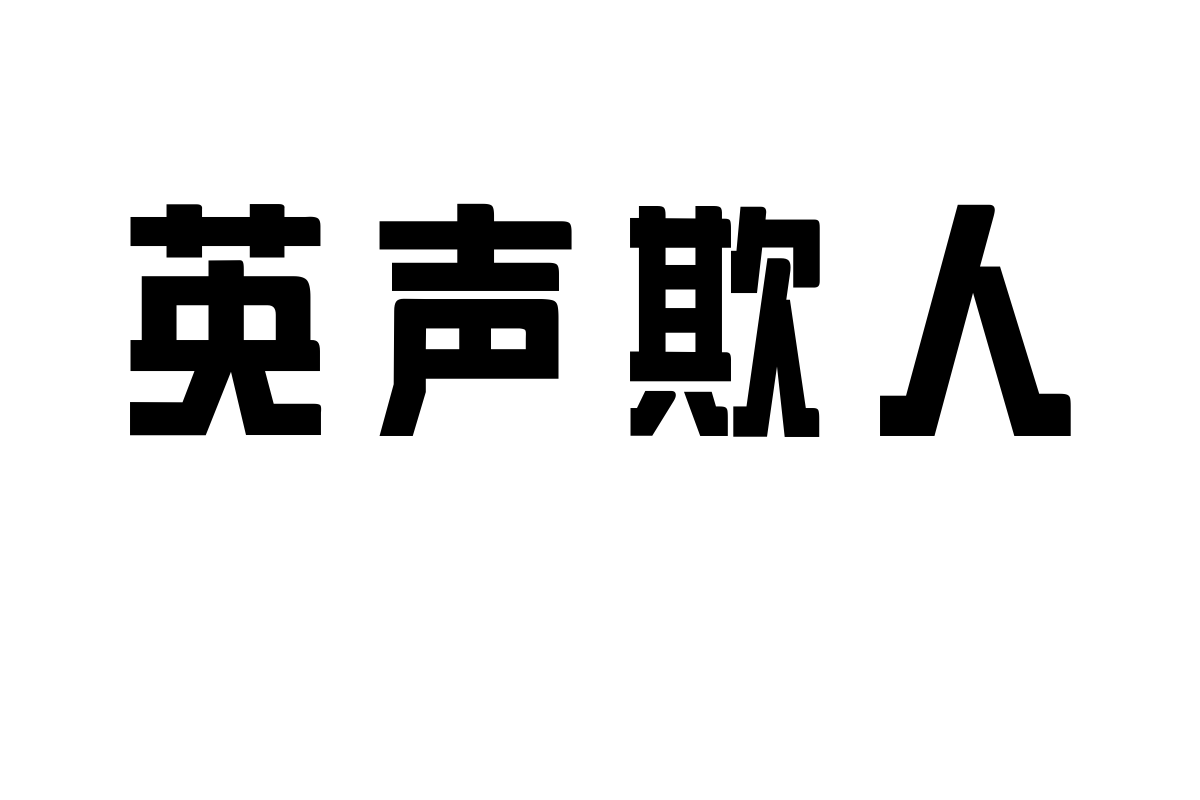
文道积木体是一种独特的字体,它融合了现代和传统的元素,创造出一种独特的视觉体验。这种字体以其独特的结构和设计而闻名,使得它在各种设计和印刷项目中都能表现出色。
首先,文道积木体的特点是其独特的笔画结构。它的笔画呈现出一种非线性的流动感,这使得每个字符看起来都像是由多个部分组成的。这种设计使得文道积木体在视觉上具有很高的辨识度,同时也为设计师提供了更多的创作自由度。
其次,文道积木体的字体大小可以根据需要进行调整,这使得它能够适应各种不同的应用场景。无论是用于标题、正文还是装饰性的文字,文道积木体都能够提供合适的大小和样式。
此外,文道积木体的可扩展性和灵活性也是其一个重要的特点。这种字体的设计允许设计师根据需要添加或删除某些部分,从而创造出新的字体样式。这使得文道积木体成为了一个真正的创意工具,能够满足不同设计师的需求。
总的来说,文道积木体是一种独特而强大的字体,它以其独特的笔画结构和可扩展性而受到设计师的喜爱。无论你是需要进行品牌标识设计、广告设计还是其他任何类型的设计项目,文道积木体都可能是你需要的优秀选择。